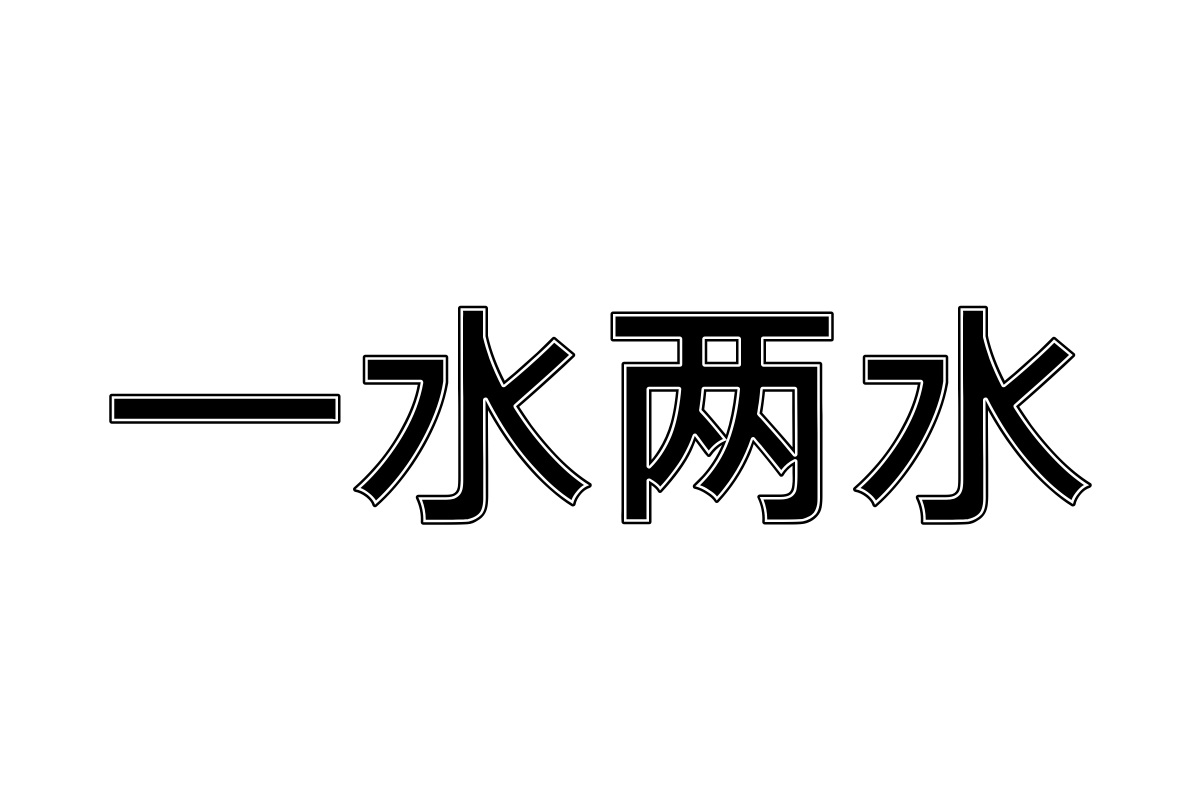
三极精描字体是一款由上海三极电子科技有限公司设计开发的中文简体字体。这款字体以其独特的风格和特点,深受广大用户的喜爱和认可。
三极精描字体的特点主要有以下几点:
1. 字形美观:三极精描字体的字形结构紧凑,线条流畅,给人以简洁、明快的感觉。同时,字体的大小适中,易于阅读,适合各种场合使用。
2. 易读性强:三极精描字体的笔画粗细适中,不易产生视觉疲劳。此外,字体的间距也恰到好处,使得文字之间的排列更加整齐,提高了可读性。
3. 适用范围广:三极精描字体适用于各种印刷品、广告、包装等场景。无论是在报纸、杂志、书籍还是网页设计中,都能展现出其独特的魅力。
4. 支持多语言:三极精描字体不仅支持简体中文,还支持其他多种语言的输入和显示。这使得用户可以根据自己的需求,选择适合自己的字体样式。